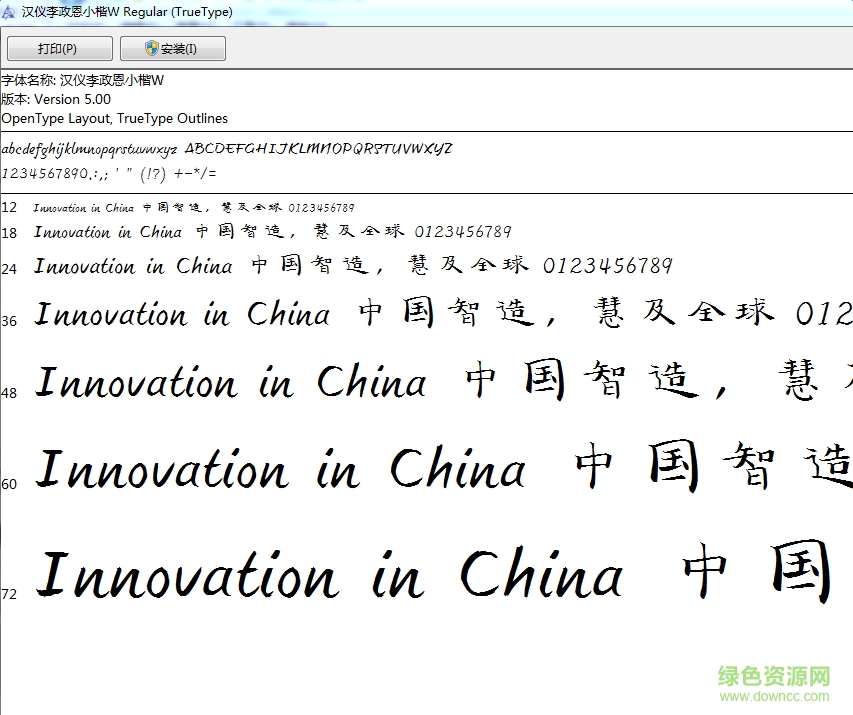
漢儀李政恩小楷字體是一款漢儀類優(yōu)雅楷體風(fēng)格字體軟件,李政恩小楷體筆畫工整,粗細(xì)不一,完美闡釋了楷體文雅特色,深受廣大書法家喜愛,還有更多好看字體歡迎來綠色資源網(wǎng)下載體驗(yàn)!
漢儀李政恩小楷字體是一款應(yīng)用于藝術(shù)設(shè)計(jì)方面的簡(jiǎn)體中文字體,該字體筆畫細(xì)膩,尾部的甩尾有力且有豐富的筆觸細(xì)節(jié),大字效果突出且引人注目;并且最大程度還原作者書寫字形,細(xì)節(jié)表現(xiàn)完整,且字庫(kù)完整,可以廣泛應(yīng)用于名片設(shè)計(jì)、新聞媒體、宣傳海報(bào)、ppt、影視制作以及內(nèi)容用字等領(lǐng)域。